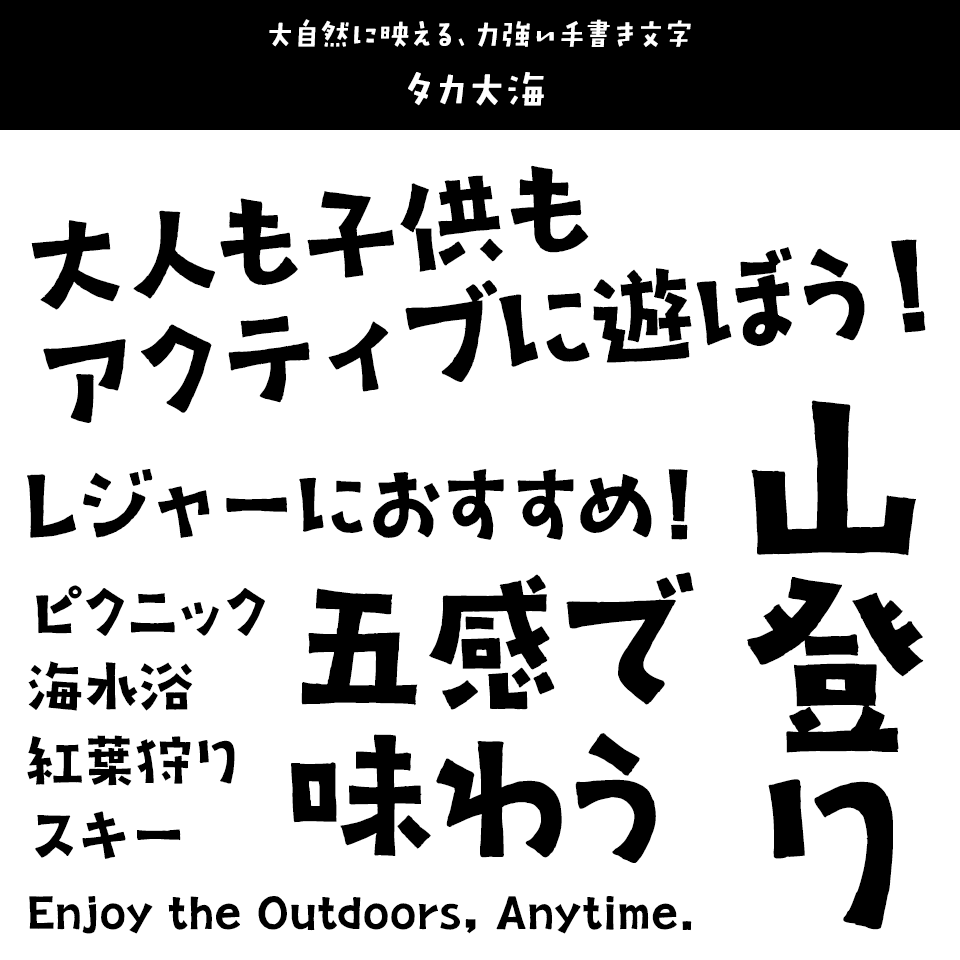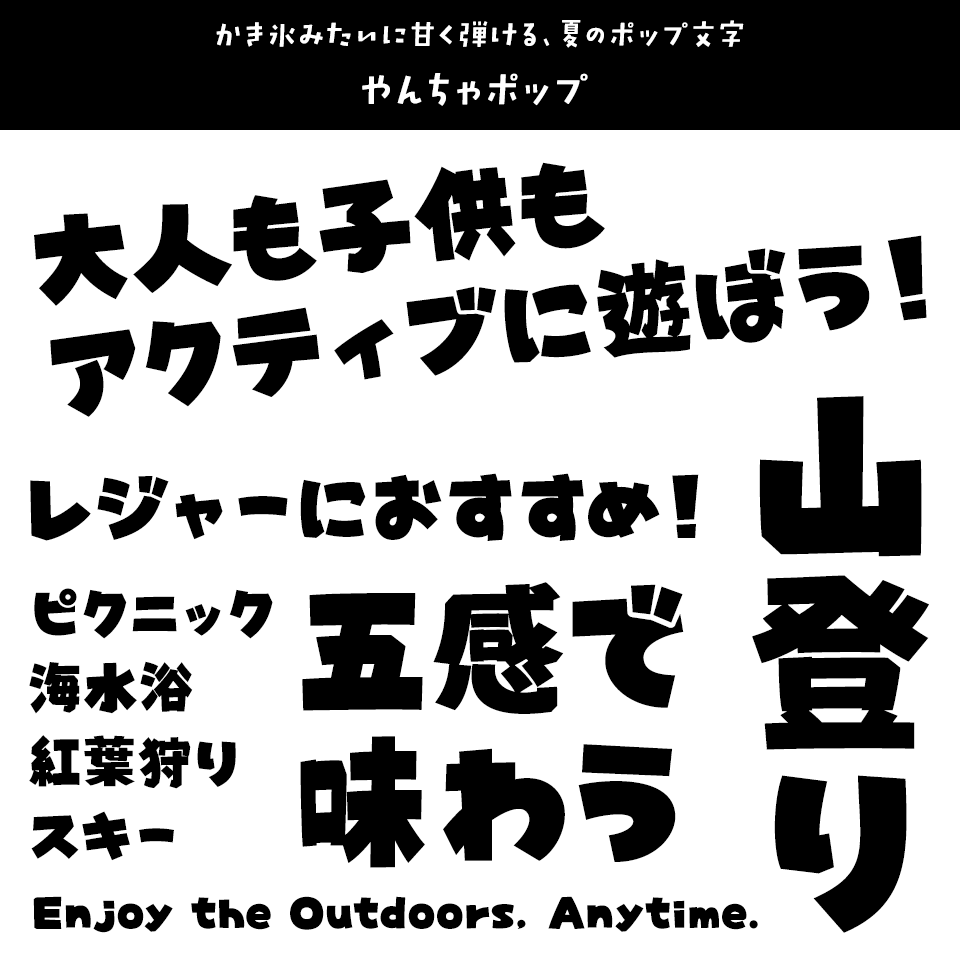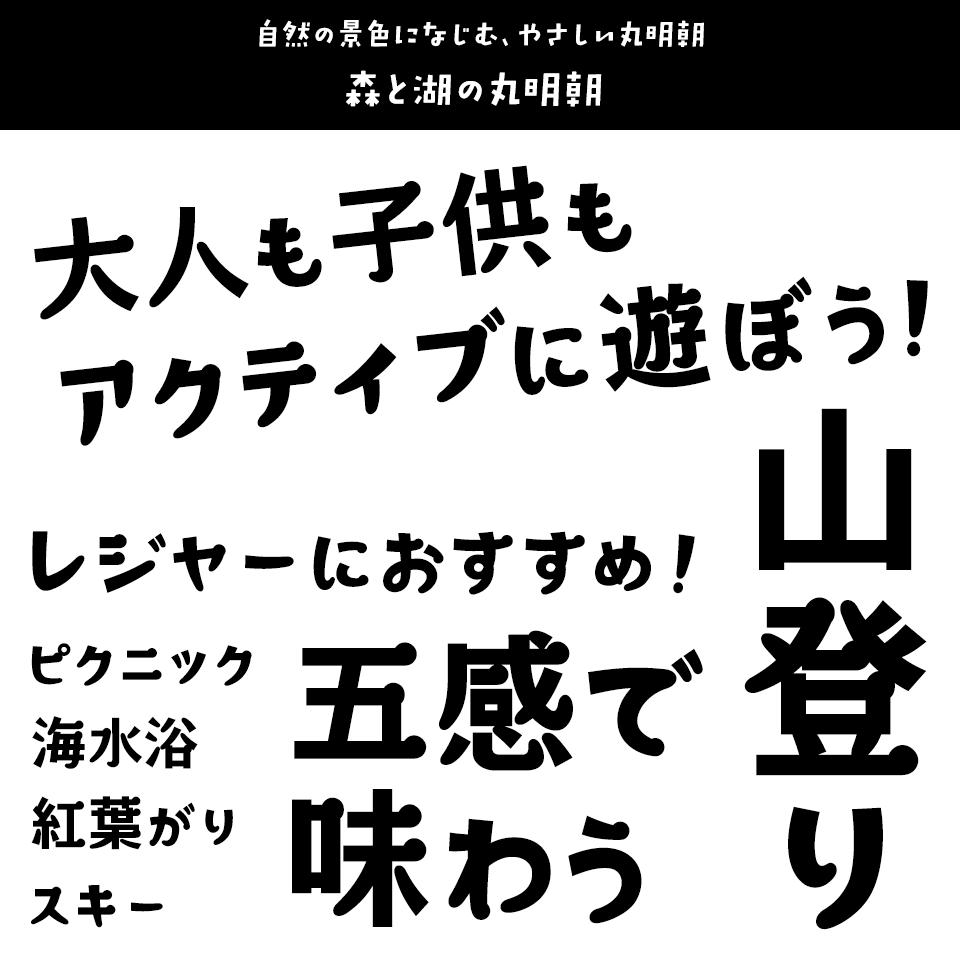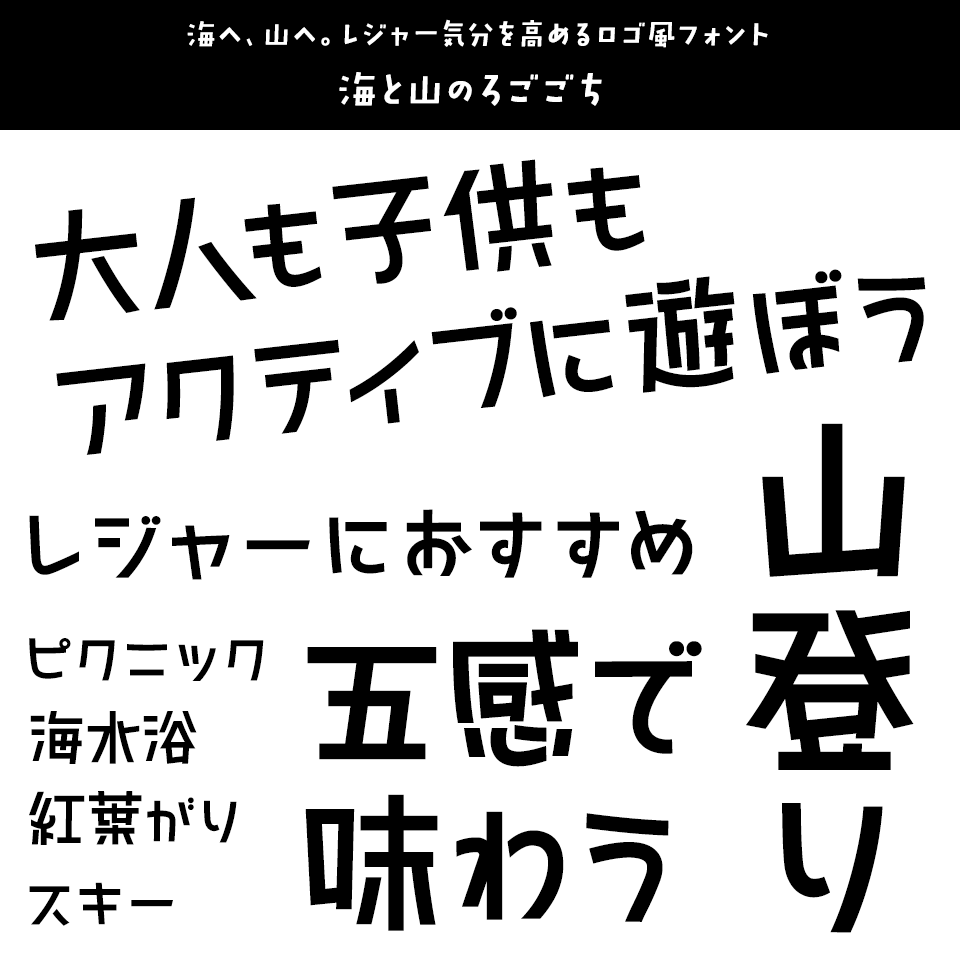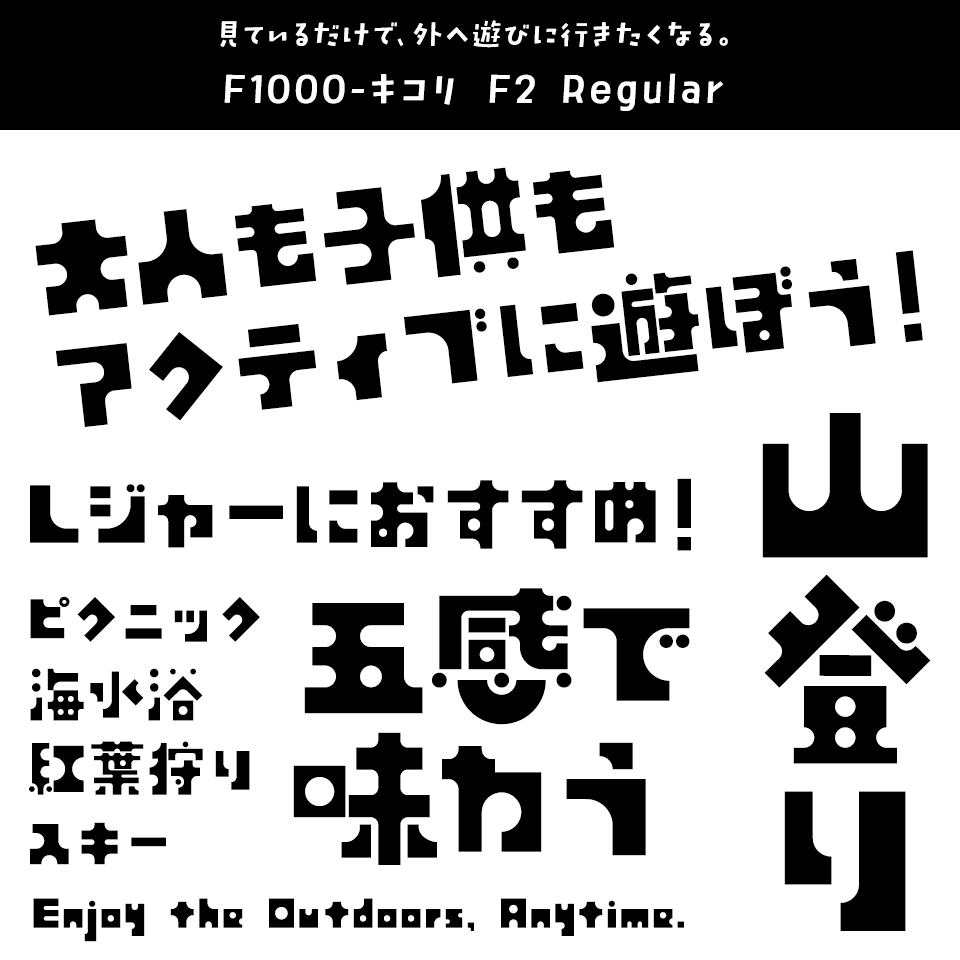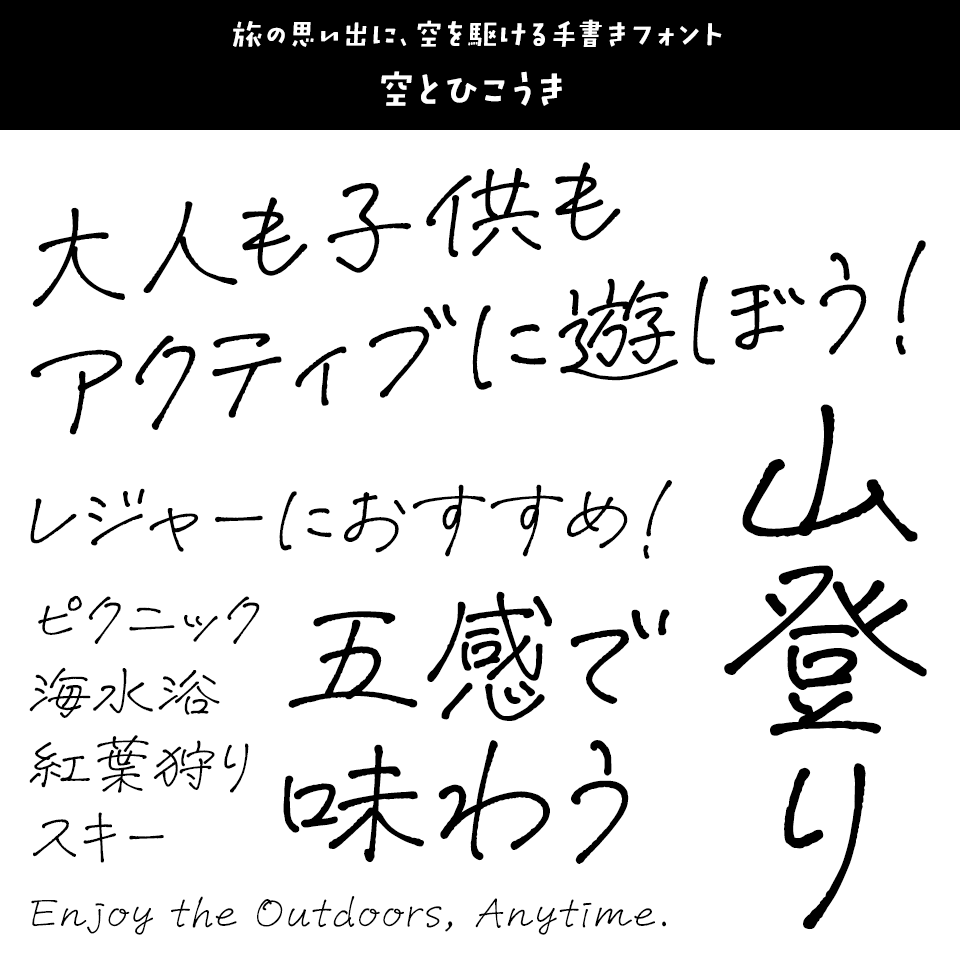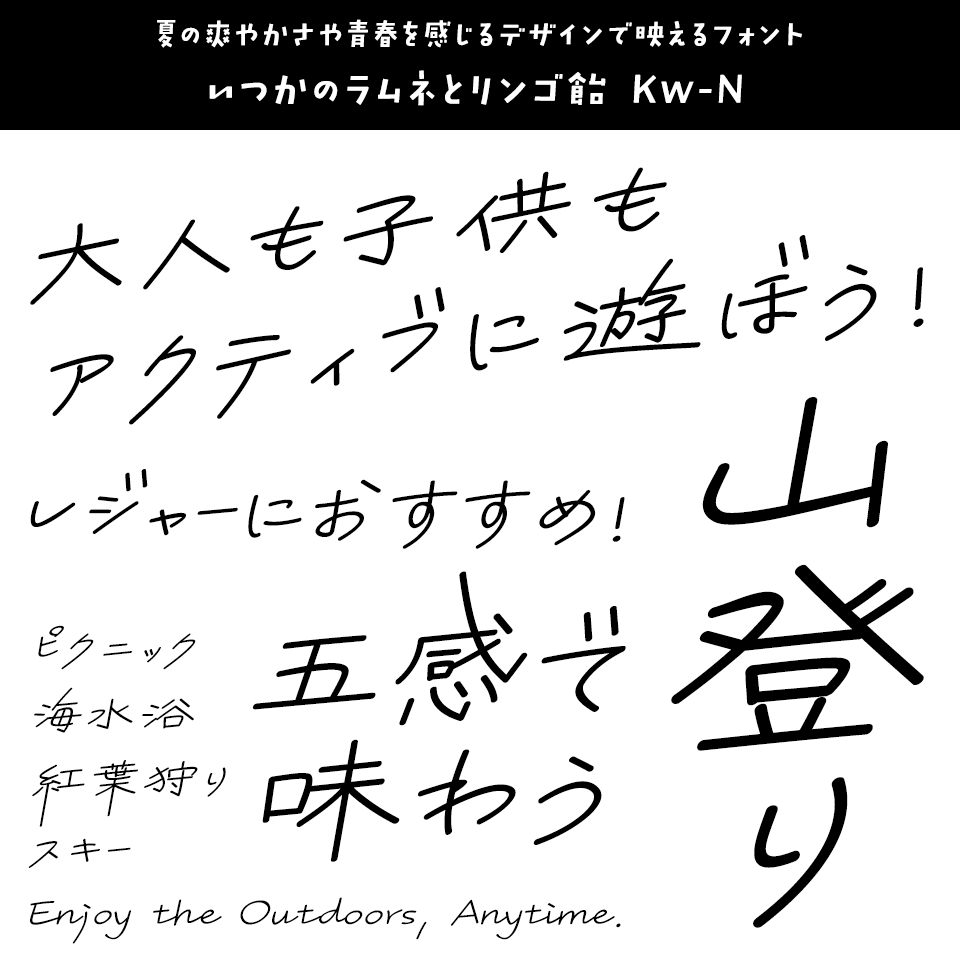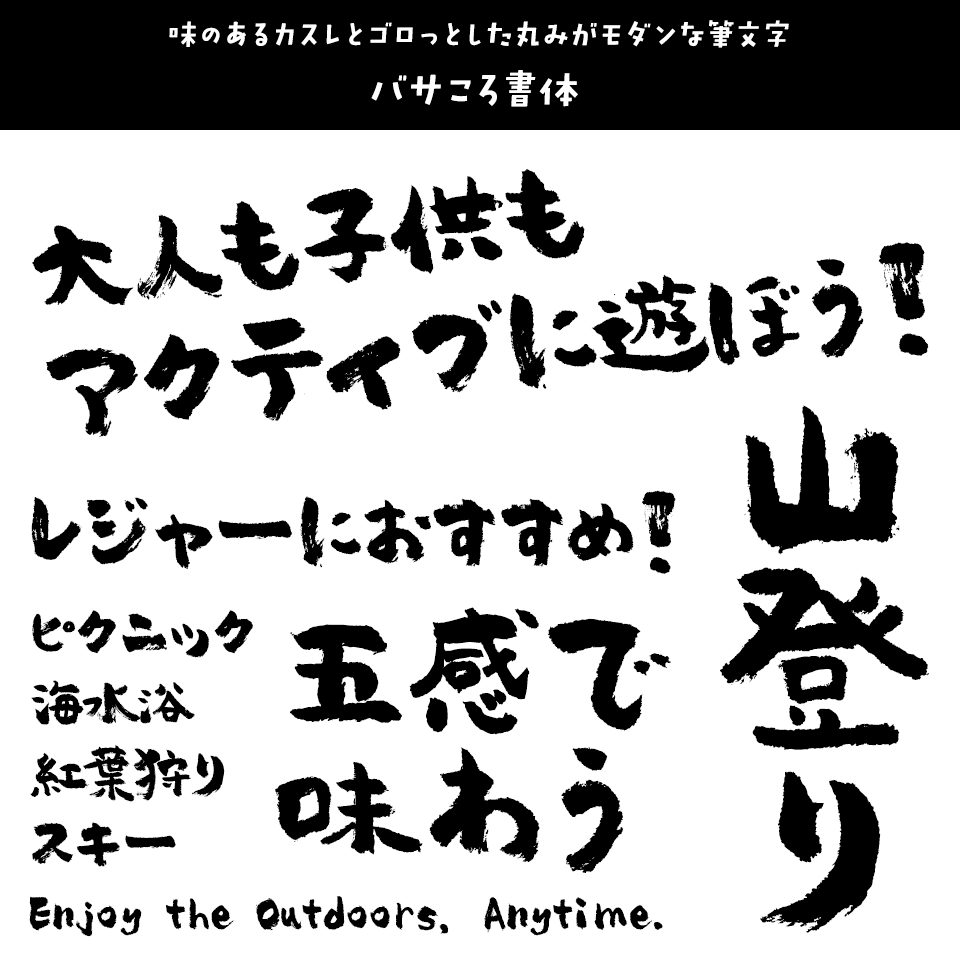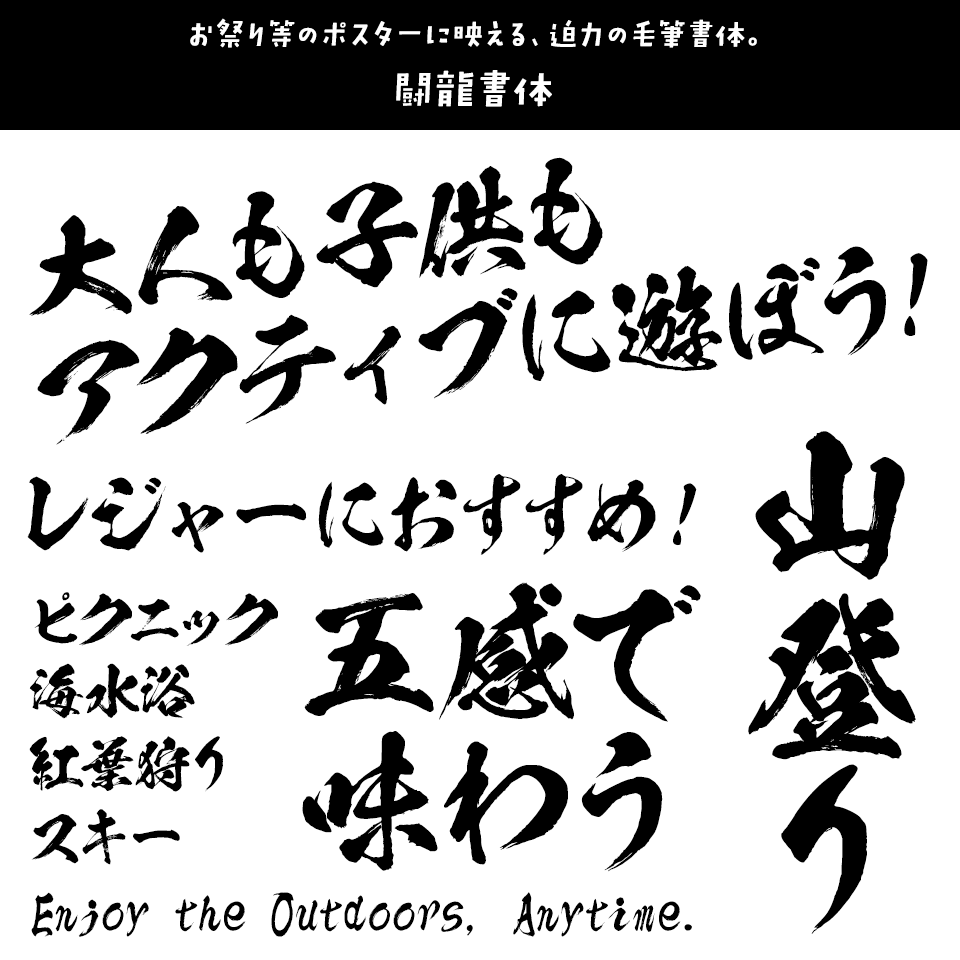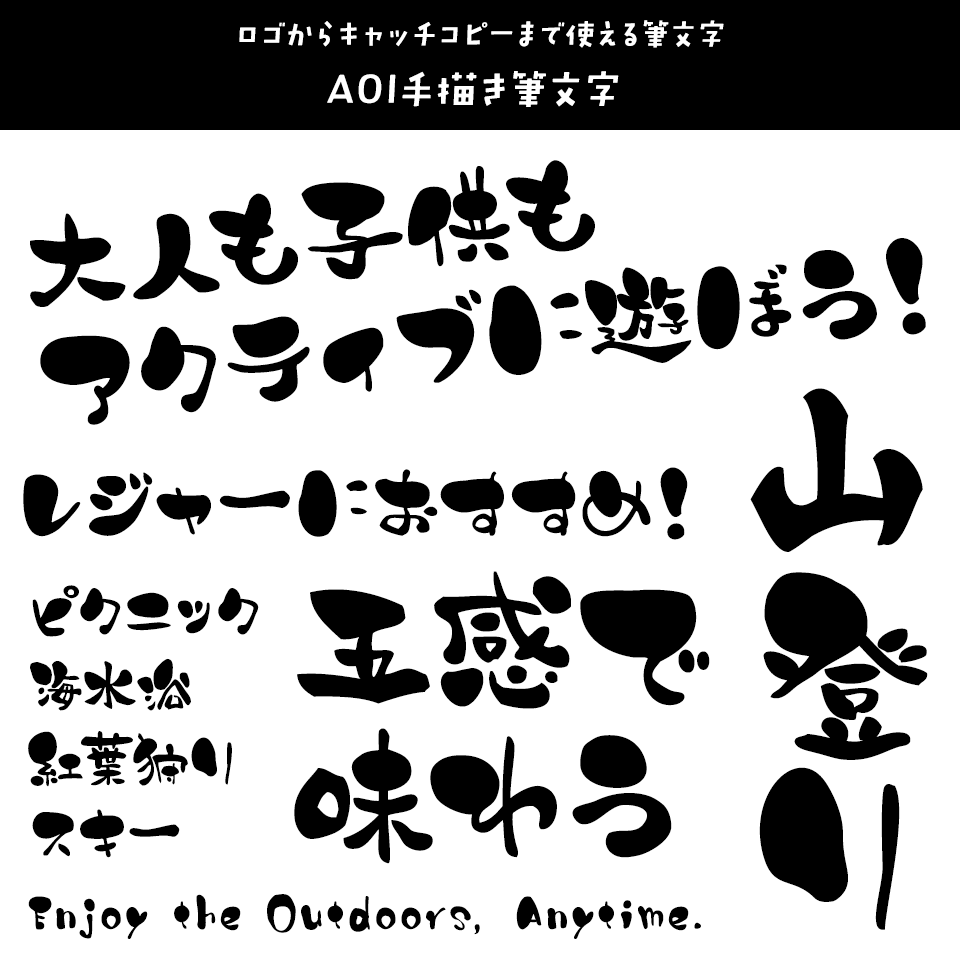
レジャーに合うフォント:特化型 目的別フォントガイド #186
今回はレジャーに合うフォント。日々フォントのことばかり考えている当店スタッフが直感的に選んだフォントをご紹介します。
レジャーに合うフォントをスタッフが選びました
レジャーに合うフォント タカ大海
大自然に映える、力強い手書き文字
レジャーに合うフォント タカ大海
アナログ感あふれる力強い筆致が、海や山など開放感のあるレジャーシーンにぴったり。ポスターやイベントタイトル、旅の思い出を印象的に残したいデザインで活躍します。
レジャーに合うフォント やんちゃポップ
かき氷みたいに甘く弾ける、夏のポップ文字
レジャーに合うフォント やんちゃポップ
子どものような元気さと親しみやすい表情が魅力。夏のイベントや親子レジャー、夏祭りの告知はもちろん、甘酸っぱい恋を描く同人誌やポスターのタイトルまで、明るく楽しい雰囲気をポップに演出します。
レジャーに合うフォント 森と湖の丸明朝
自然の景色になじむ、やさしい丸明朝
レジャーに合うフォント 森と湖の丸明朝
丸みのある文字が、森や湖など自然の風景と相性抜群。アウトドアや観光案内、旅行アルバムなど、やさしく落ち着いた雰囲気を演出したいときにおすすめです。
レジャーに合うフォント 海と山のろごごち
海へ、山へ。レジャー気分を高めるロゴ風フォント
レジャーに合うフォント 海と山のろごごち
タイピングしただけで、作字風のロゴタイプが完成するフォント。キャンプ、アウトドア、旅行などの楽しい雰囲気にぴったり。アウトドア雑誌にありそうなおしゃれなフォントです。
レジャーに合うフォント F1000-キコリ F2 Regular
見ているだけで、外へ遊びに行きたくなる。
レジャーに合うフォント <strong>F1000-キコリ F2 Regular</strong>
木や森を連想させる、素朴で遊び心のある文字が魅力。見ているだけで外へ遊びに行きたくなるような楽しさがあり、キャンプや森あそび、自然体験などのレジャー告知とも相性マルです。
レジャーに合うフォント 空とひこうき
旅の思い出に、空を駆ける手書きフォント
レジャーに合うフォント 空とひこうき
空へ伸びる飛行機雲を思わせる、軽やかな手書きフォント。旅行写真やキャンプ、レジャーの思い出を彩るデザインにぴったりで、手書きの温もりを自然にプラスできます。
レジャーに合うフォント いつかのラムネとリンゴ飴 Kw-N
夏の爽やかさや青春を感じるデザインで映えるフォント
レジャーに合うフォント いつかのラムネとリンゴ飴 Kw-N
ノスタルジックでエモい雰囲気を持つフォント。横長の文字でありつつも、時々上下に大きく飛び出すデザイン。
レジャーに合うフォント バサころ書体
味のあるカスレとゴロっとした丸みがモダンな筆文字
レジャーに合うフォント バサころ書体
筆文字独特のかすれとゴロっとした筆文字で 温かみや親しみやすさを感じます。和を感じるシーンで使いたいモダンでスタイリッシュなフォントです。
レジャーに合うフォント 闘龍書体
お祭り等のポスターに映える、迫力の毛筆書体。
レジャーに合うフォント 闘龍書体
力強さや躍動感を出したいデザインにぴったり。文字だけでインパクトを出せるので、ポスター、縁日POP、屋台メニュー、和風イベントのタイトルなど幅広いシーンで活躍できます。
レジャーに合うフォント AOI手描き筆文字
ロゴからキャッチコピーまで使える筆文字
レジャーに合うフォント AOI手描き筆文字
伝統的な筆致と現代的な使いやすさが融合した魅せる筆文字。お祭りの看板やメニューなどに大活躍です。